97 Schriftarten Tattoo Namen
Schrift Tattoo 20 Tattoo Ideen Fur Schriftzuge
Die tattoos haben im laufe des lebens eines menschen für unzählige dinge gedient.
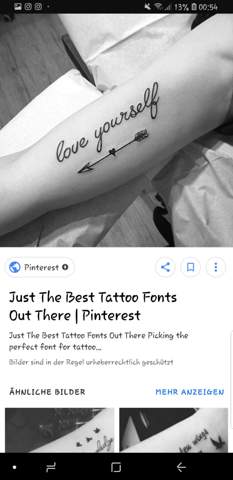
Schriftarten tattoo namen. Find and download the right font for your next tattoo. Lettering styles include tribal traditional sailor blackletter fancy cursive script etc. Liebe manche menschen tätowieren sich das datum an dem.
Die schriftarten für tattoos sind zahlreich und deshalb fällt die entscheidung für die passende schrift manchmal schwer. Schreibe hier mit unserem fraktur schriftgenerator wörter namen und schriftzüge für tattoos in schöner altdeutscher schrift einfach selbst. Reine text tattoos liegen heute immer mehr im trend und immer mehr menschen wählen worte namen kurze zitate oder bedeutsame redewendungen um sich durch ihre tattoos auszudrücken.
Egal ob sie sich einen namen ein lebensmotto oder inspirierendes zitat stechen lassen ist die schriftart von zentraler bedeutung. Tattoo schriftarten können verwendet werden um sich eine vorschau für textbasierte tätowierungen zu erstellen und so einfacher über diese zu entscheiden. Herzlich willkommen schriftzug generator tattoo.
Einige der wichtigsten bedeutungen für diejenigen die sich tätowieren lassen haben waren.